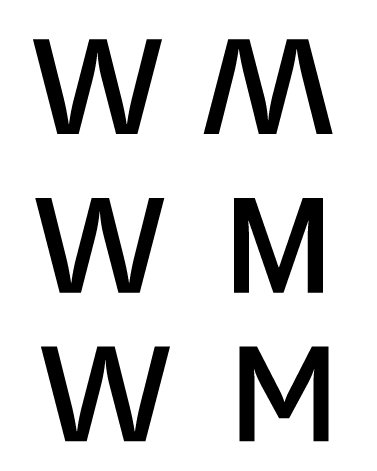
Signaletica stellt sich der Kritik
Jenes ist dein kleines k:
Das besitzt genau die formale Form des "untauglichen" K. Warum?
… Testen kann ich es nicht. …
Da kann ich mich nur Ralf anschließen. Du entwickelst Formen mit deinen Augen für Menschen, die sie nicht sehen können. Der einzige Weg, zu einem für die Zielgruppe brauchbaren Ergebnis zu kommen, ist, die Schrift zu testen.
(Du merkst, ich gehe immer noch davon aus, dass der Spagat zwischen einem guten Ergebnis für Sehende und Nicht-Sehende nicht möglich ist. Drum meine Konzentration auf die Nicht-Sehenden. Die anderen können’s salopp gesagt eh lesen.)
Jetzt bist Du aber wieder bei den Minuskeln ;)
Richtig :-) Liegt daran, dass ich auf die Schnelle keine Schrift kenne, bei der sich k und K formal unterscheiden. Darum meine Frage. ;-)
Da kann ich mich nur Ralf anschließen. Du entwickelst Formen mit deinen Augen für Menschen, die sie nicht sehen können. Der einzige Weg, zu einem für die Zielgruppe brauchbaren Ergebnis zu kommen, ist, die Schrift zu testen.
(Du merkst, ich gehe immer noch davon aus, dass der Spagat zwischen einem guten Ergebnis für Sehende und Nicht-Sehende nicht möglich ist. Drum meine Konzentration auf die Nicht-Sehenden. Die anderen können’s salopp gesagt eh lesen.)
Ich bin davon überzeugt, dass das Ergebnis für beide Gruppen eine gute Lesbarkeit gewährleistet.
Es bleibt spannend … ;-)
Ich bin davon überzeugt, dass das Ergebnis für beide Gruppen eine gute Lesbarkeit gewährleistet.
Zumindest kann es das. Wie schon an anderer Stelle gesagt: Wir haben in den letzten Jahren zusammen mit dem DBSV die DIN-Norm zur Leserlichkeit überarbeitet und dabei keine Unterscheidung zwischen gut und schwach sehenden eingebaut. Die Prinzipien sind die gleichen, nur der Schwellenwert, ab dem Informationen leserlich/unleserlich werden ist unterschiedlich. Für die taktile Blindenschrift kann das auch gelten – sie ist ja eben gerade keine Sonderschrift (wie Braille) mit individuellem Design, sondern einfach eine taktile Abbildung des üblichen Buchstabenskeletts.
sie ist ja eben gerade keine Sonderschrift (wie Braille) mit individuellem Design, sondern einfach eine taktile Abbildung des üblichen Buchstabenskeletts.
Ich habe ja bereits geschrieben, dass es einige Punkte zu berücksichtigen gilt. Die DIN ist in Sachen Barrierefreie Leitsysteme nicht auf dem neusten Stand.
Das die Leserlichkeit für Schehrsehbehinderte keine anderen Anforderungen an die Schrift hat wie für normal sehende Menschen ist ja auch klar und auch von mir bereits angesprochen wurden.
Es gibt Schriften, die für eine gute Leserlichkeit auf Entfernung optimiert sind, genauso wie es Schriften gibt, deren Versalien besser zu ertasten sind, als die anderer Schriften. Ich würde diese beiden Punkte gern kombinieren. Dazu gilt es ja lediglich bestimmte Punkte zu berücksichtigen.
Du entwickelst Formen mit deinen Augen für Menschen, die sie nicht sehen können.
das wäre doch mal ein interessanter ansatz:
was käme bei einer studie herraus, wenn man die sehbehinderten die buchstaben 'entwerfen' lässt?
ich glaube das hat auch viel mit lernprozess zu tun, je nachdem wie du die form entwickelst, so werden sich die sehbehinderten an dieser form festhalten und diese auch lernen. ich glaube für einen blinden oder sehbehinderten ist es weniger wichtig ob das M ausgestellt ist oder nicht, gerade beim M gibt es da wenig verwechslungsgefahr. auch beim G und K, der blinde tastest diese form ab und lernt sie dementsprechend.
. ich glaube für einen blinden oder sehbehinderten ist es weniger wichtig ob das M ausgestellt ist oder nicht, gerade beim M gibt es da wenig verwechslungsgefahr. auch beim G und K, der blinde tastest diese form ab und lernt sie dementsprechend.
Das M sollte konisch zusammenlaufen ebenso wie das W. Somit können diese Buchstaben einfach von einander unterschieden werden und auch vom H mit seinen prallel laufenden Strichen unterschieden werden.
du widersprichst dir selbst.
wenn das M und das W konisch geformt werden, dann sind diese ja ebenfalls nicht voneinander
unterscheidbar, wäre es nicht sinvoller dann einen der beiden nicht konisch zu formen um die
unterscheidbarkeit noch mehr hervorzuheben?
mal abgesehen davon das ein W ja ein auf dem kopf stehendes M ist und die unterscheidbarkeit
somit schon von hause aus gegeben ist. es sei denn die buchstaben hängen nicht an der wand sondern
liegen im raum aber selbst dann folgen ja andere buchstaben die das erkennen leichter machen oder
man gibt andere hilfsmittel an, an denen sich die sehbehinderten orientieren können, z.b. ein hilfsmittel
für den betrachtungswinkel.
wieso ein M oder ein W mit einem H verwechselt werden kann, verstehe ich als nicht sehbehinderterter gerade
nicht, das ist genau dieser lernprozess von dem ich oben gesprochen habe, der muss so oder so passieren.
Verschieden Formen gestalten und diese taktil ausgearbeitet zum Testen vorlegen. ...
Daher meine Frage nach der "Winkelauflösung" beim Tasten, ob nur 0/45/90 oder auch Zwischenwerte zuverlässig möglich sind.
1. Strich Deines M: Hmmm... schräg oder senkrecht? --> mal weiter tasten
2. Strich: spitzer Winkel dazu ohne Querstrich --> A scheidet aus, M und N bleiben, erster Strich muss senkrecht gewesen sein
3. Strich: noch ein spitzer Winkel, parallel zum ersten -> Ahja, ganz klar ein N ... Weiter zum nächsten Buchstaben
4. Strich: Schräg zum N, Anfang eines V oder W?
Oops, zu Ende ... Was war denn das nun?!?